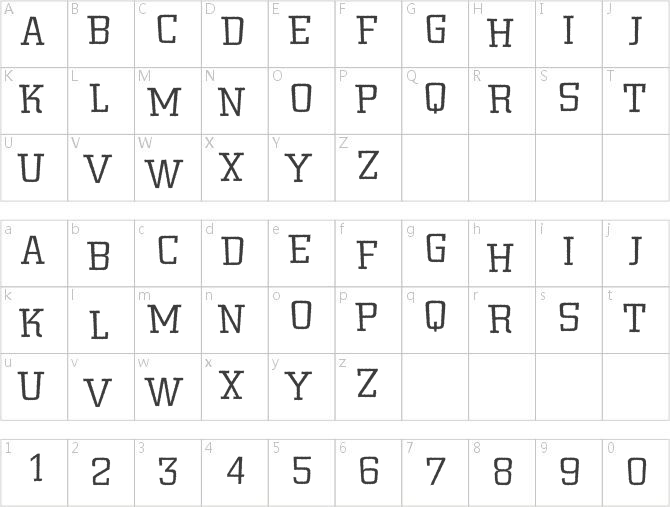
a_CityNovaTitulRgLt 詳情頁
a_CityNovaTitulRgLt字體字庫是一款讓人賞心悅目、百看不厭的英文字體,適合各類廣告和產(chǎn)品包裝設(shè)計應(yīng)用,字體大小0.24MB,格式為ttf字體,上傳用戶是一直在守護(hù),作者/版權(quán)方為未知